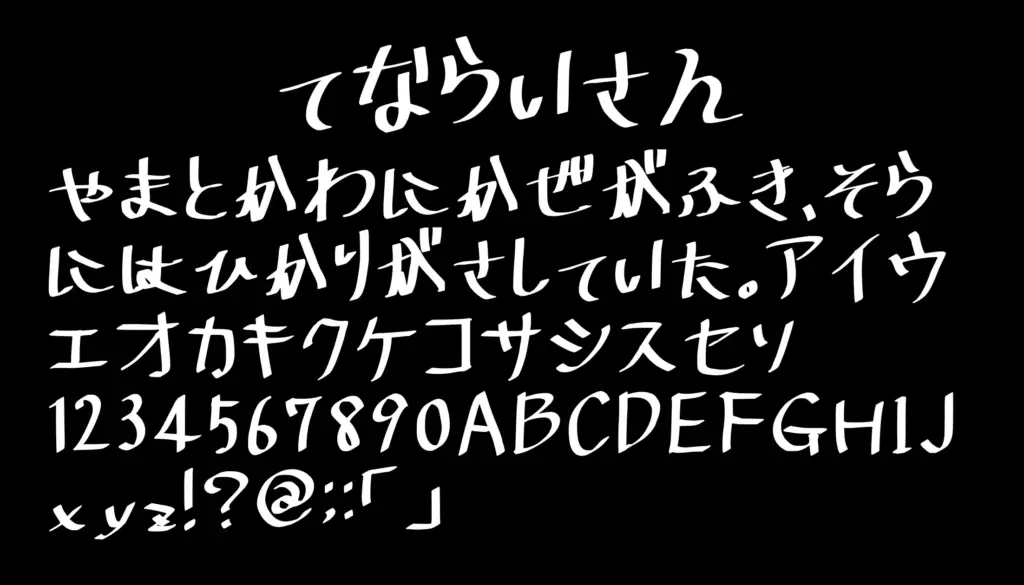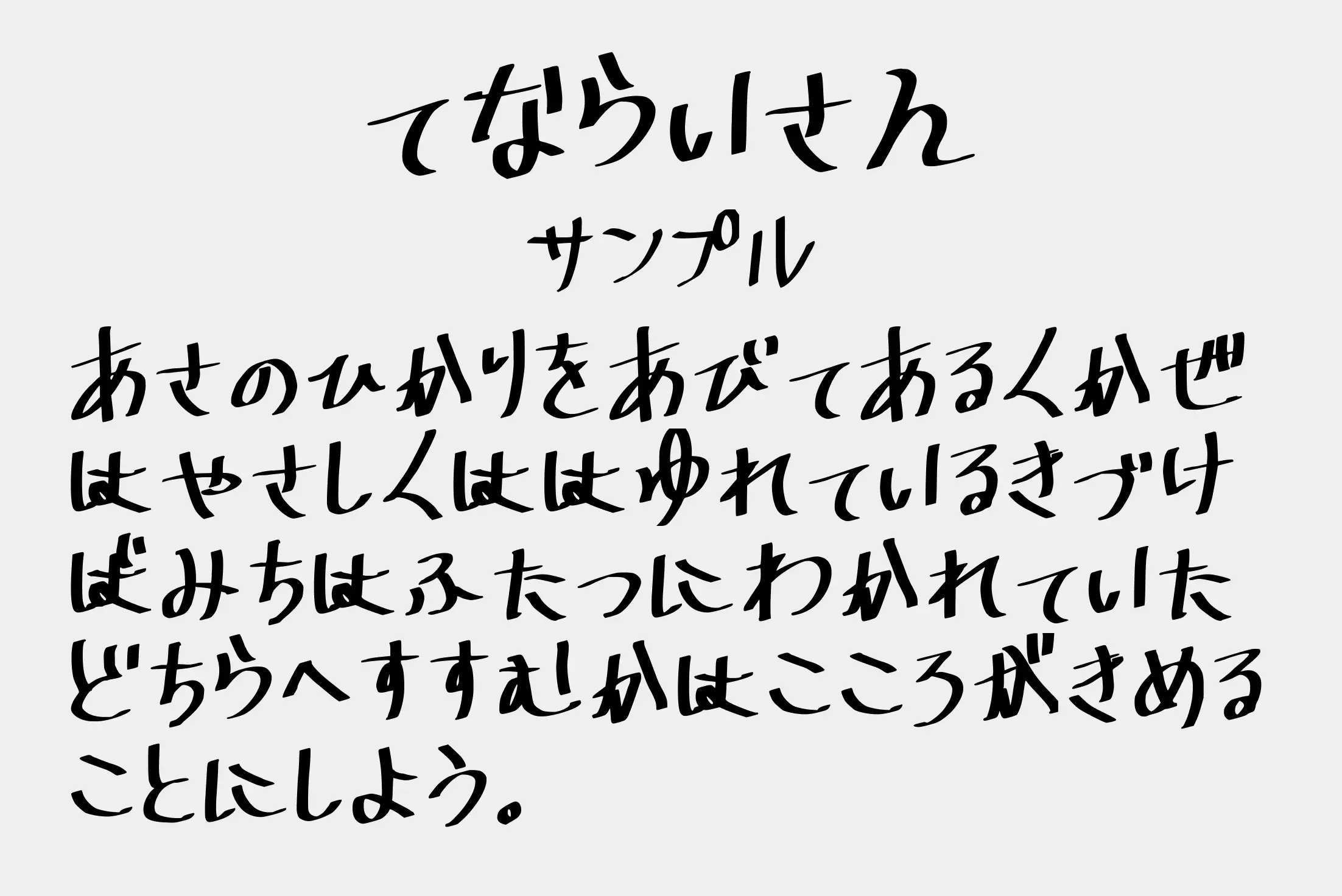
あえて崩した線のゆらぎを活かした手書き風フォントです。素朴で親しみやすい雰囲気があり、日記・イラスト・メッセージ系のデザインに相性抜群。文字の抜け感やラフさが作品に温度を添えてくれます。独特の味わいを出したい時にぴったりです。
てならいさん
| 収録文字 | ひらがな・カタカナ・英字・数字・記号 |